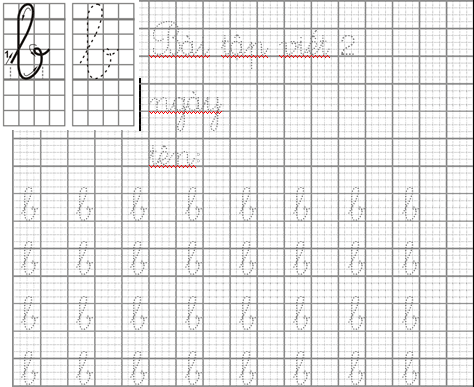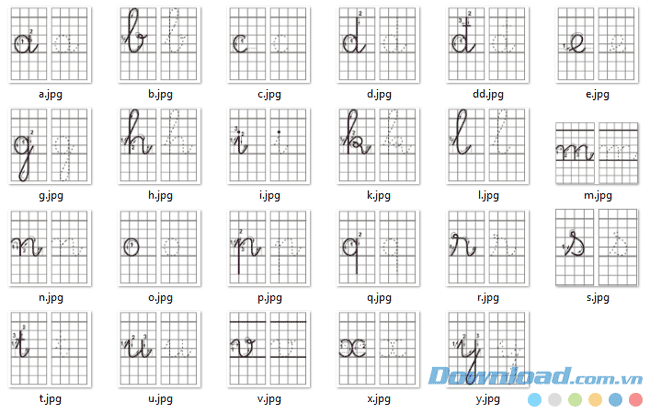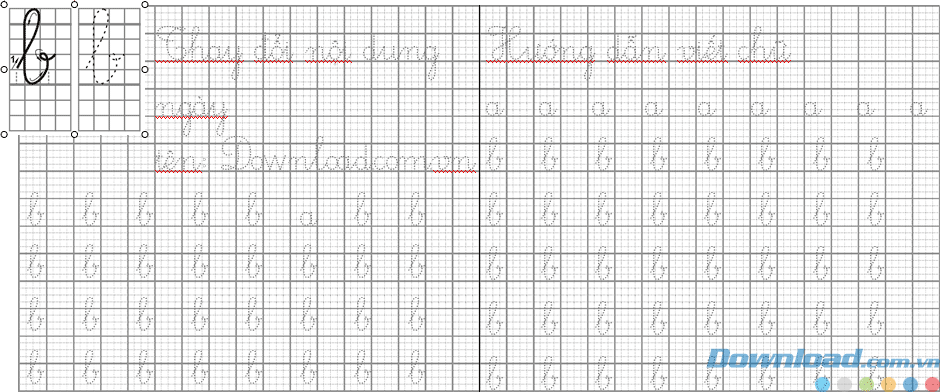
Font Unitapviet
Font Unitapviet là bộ phông chữ tập viết dành cho học sinh tiểu học. Bộ Font Unitapviet hỗ trợ tiếng Việt với nét chữ vô cùng mềm mại giống với nét chữ luyện viết
Font Unitapviet là bộ phông chữ tập viết dành cho học sinh tiểu học. Bộ Font Unitapviet hỗ trợ tiếng Việt với nét chữ vô cùng mềm mại giống với nét chữ luyện viết của học sinh lớp 1. Tải Font Unitapviet để có ngay bộ font chữ tiếng Việt luyện viết để tự tạo ra các trang viết tô chữ miễn phí.
Chắc hẳn ai cũng đã từng sử dụng các cuốn vở tập tô chữ khi bắt đầu vào lớp 1. Tuy nhiên với bộ Font Unitapviet chúng ta có thể tạo ra các trang tô chữ theo cách riêng của mình. Có thể là những chữ cái nhưng cũng có thể là một cụm từ, một câu, vv theo cách mình mong muốn để in cho con em ngay lập tức.
Như bạn thấy trong hình trên, tất cả các chữ cái đều được vẽ bằng các đường nét đứt (để cho trẻ tô theo) và có hình dáng theo đúng chuẩn chữ viết trong trường tiểu học do BGD ban hành.
Với bộ font chữ UNITapviet bạn có thể
- Tạo các bài nhận biết chữ cái theo khổ lớn để cháu viết theo
- Dễ dàng in lại nhiều lần các chữ trẻ viết còn xấu để luyện viết thêm, điều đó đồng nghĩa với việc bạn tiết kiệm được một khoản chi phí.
- Tạo những bài tập viết là tên của trẻ, tên người thân... hay những gì gần gũi và có ý nghĩa với trẻ; tạo sự hứng thú cho trẻ vào những giờ tập viết ở nhà.
Bộ ảnh hướng dẫn cách viết chữ UNITapviet
Thay đổi nội dung trang luyện viết theo ý bạn